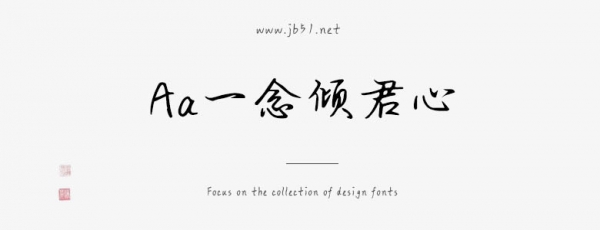
Aa一念傾君心是一款不錯的藝術(shù)字體,由Aa字庫出品,字體筆觸適中,字形端正,擁有字符數(shù)8028和字形數(shù)8008,具有很好的視覺感,適合應(yīng)用于藝術(shù)設(shè)計、平面宣傳設(shè)計、網(wǎng)頁設(shè)計,書法字帖等領(lǐng)域,需要的朋友可以前來本站下載。